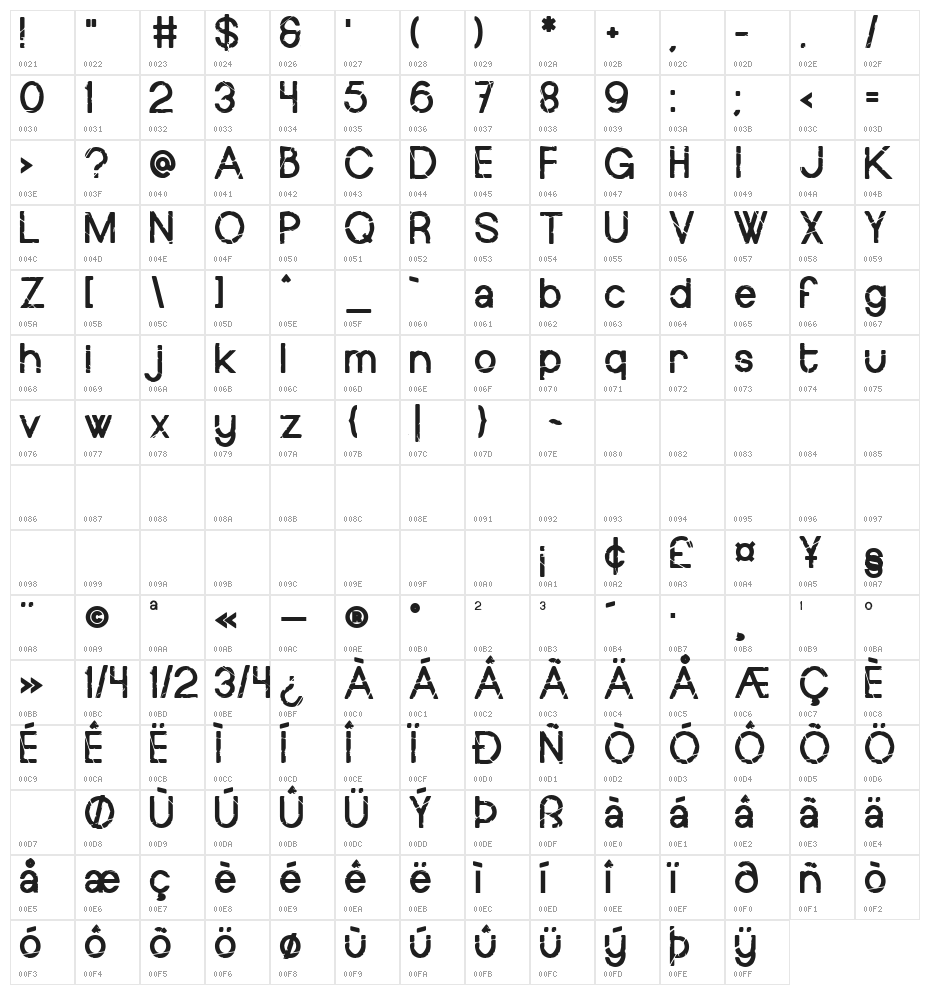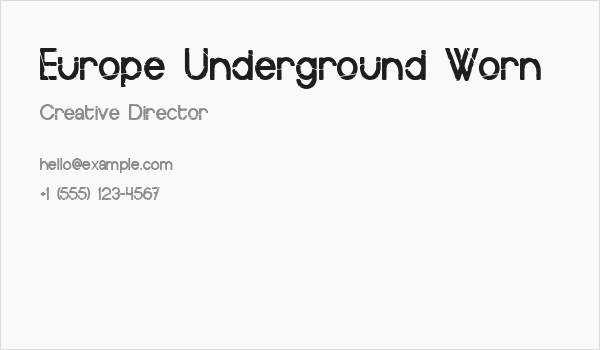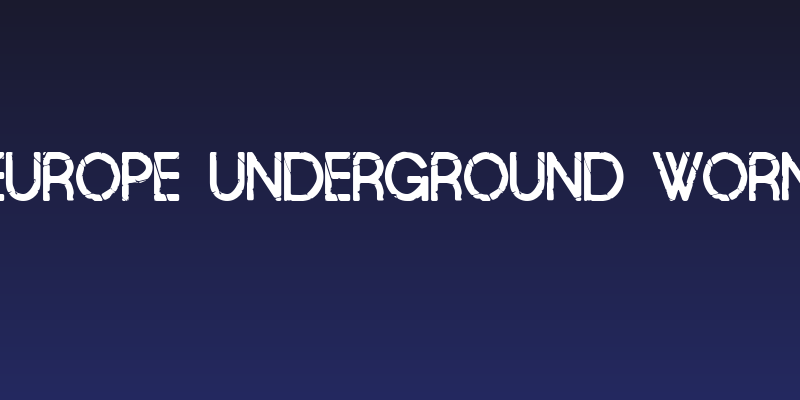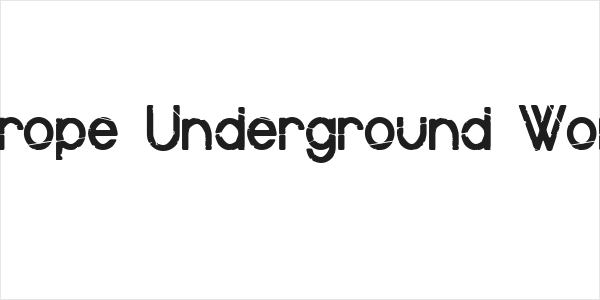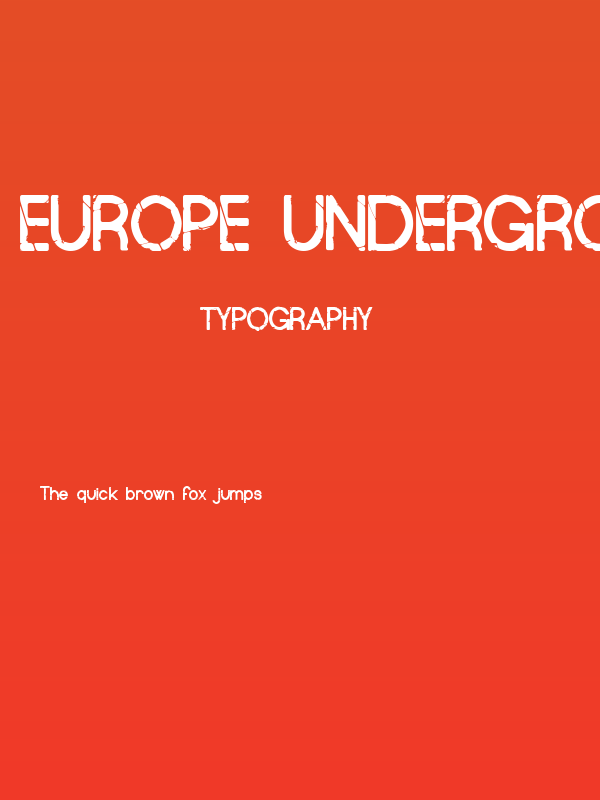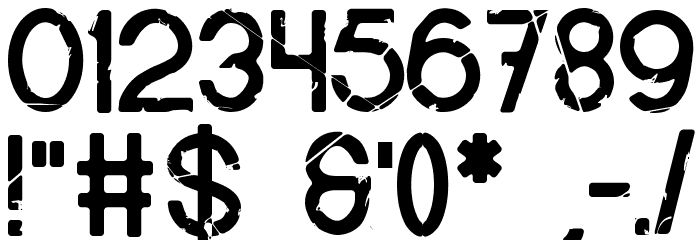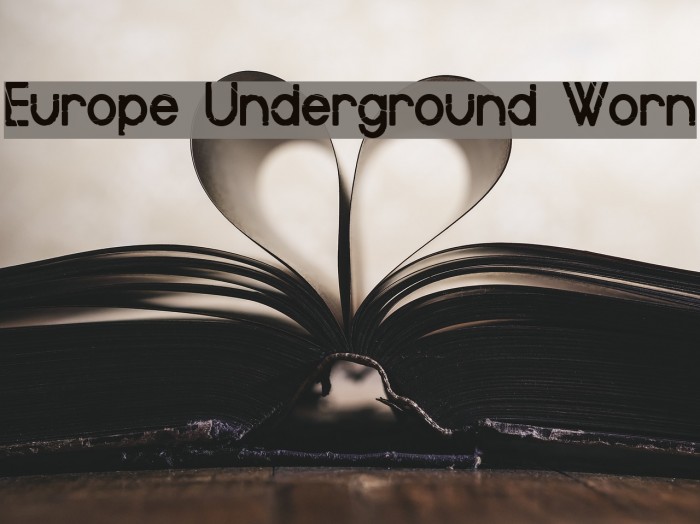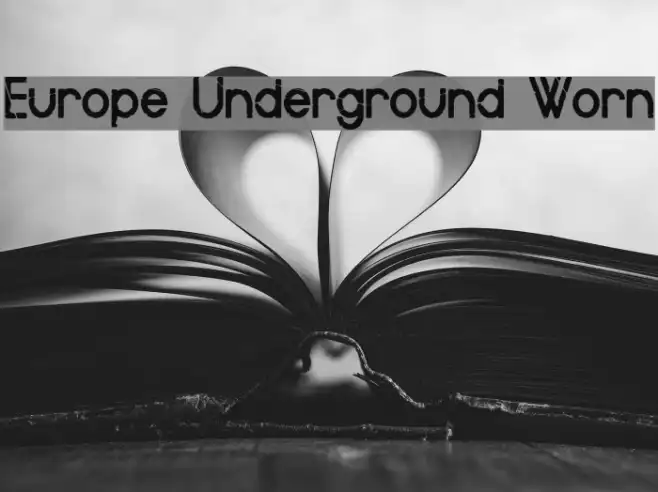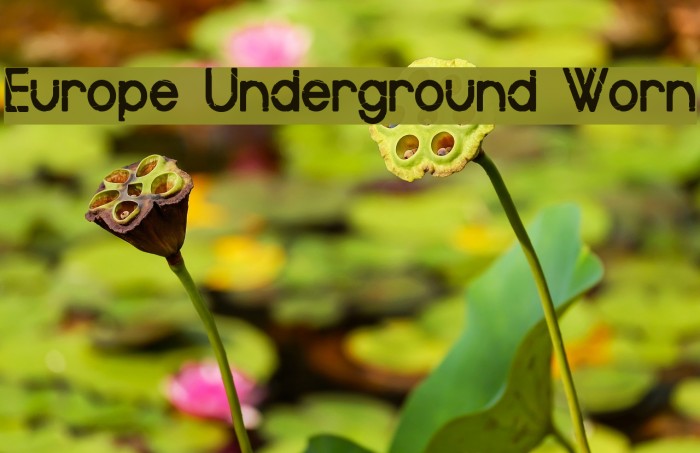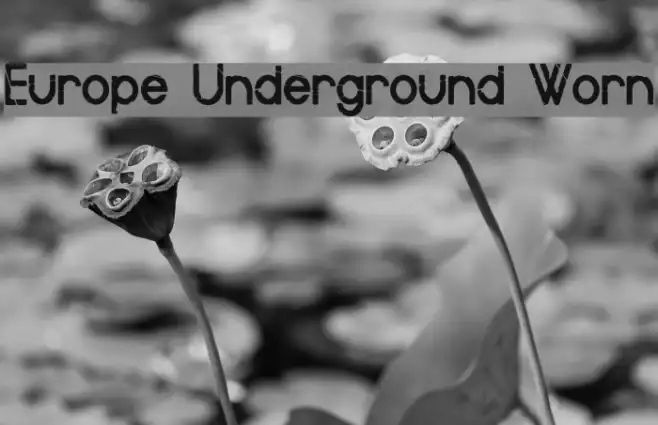
Europe Underground Worn Font
| Projets proposés | Ideal for music album covers, posters, urban-themed designs, and any project needing a raw, edgy look. |